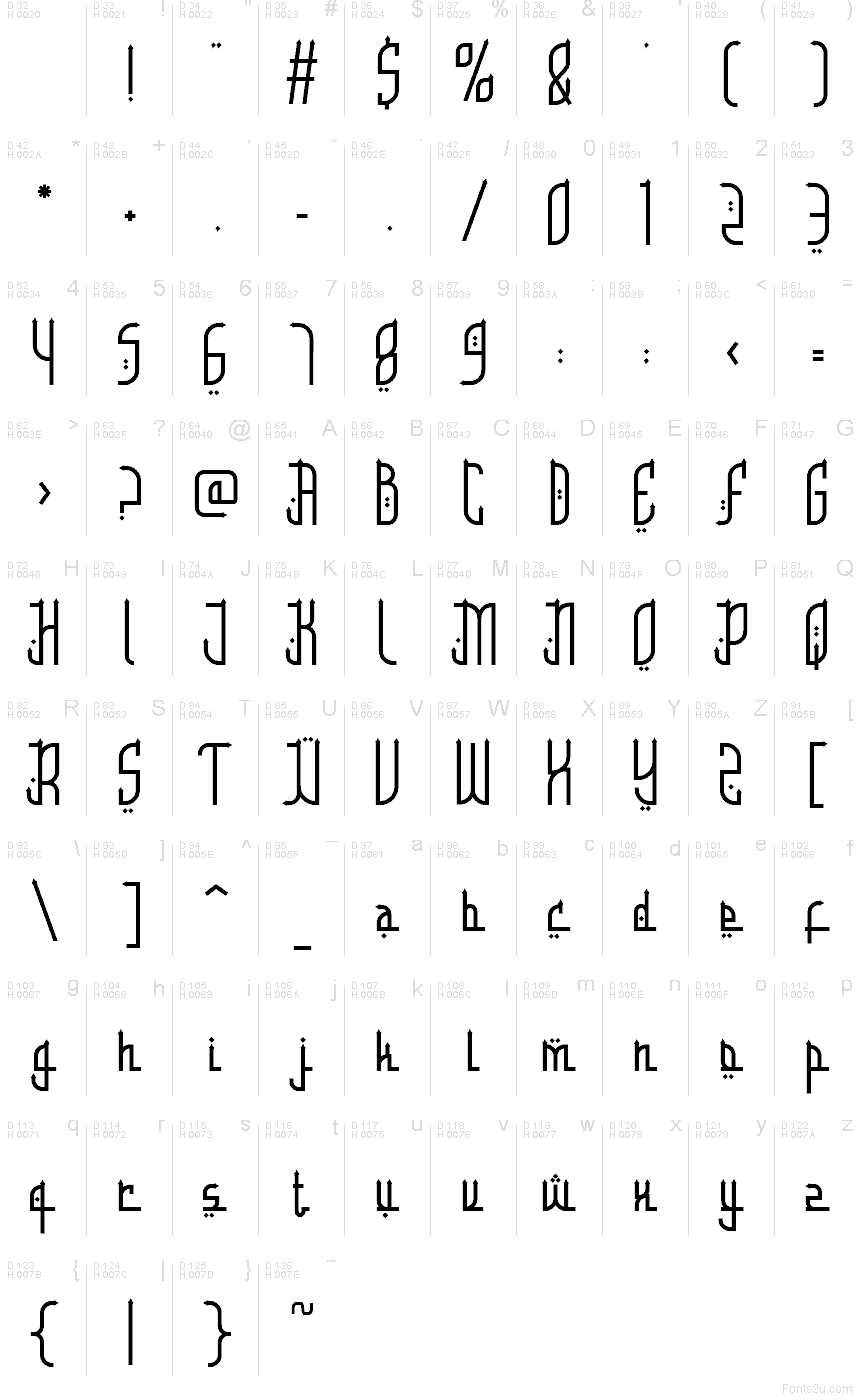
Nashir Nectar Two od Putracetol Studio je bezplatné arabské písmo typu display, které vychází z kaligrafických siluet. Kombinuje vysoké vertikální tahy, špičaté vrcholy a tečkované akcenty, čímž navazuje na tradice arabského písma. Neustálý kontrast mezi pevnými vzpřímenými liniemi a zakřivenými tvary dodává písmenům ceremoniální, až nápisový vzhled, který se vymyká běžnému neutrálnímu stylu.
Své uplatnění najde v ramadánových akcích, plakátech na akce, halal obalech, brandingu restaurací nebo grafice kulturních festivalů, kde tečky a ostré vrcholy dokážou nést téma bez potřeby dalších ozdob. Krátké titulky a loga těží zejména z jeho vzpřímeného rytmu, který dodává slovům nádech řemeslného nápisu namísto obyčejného textu.